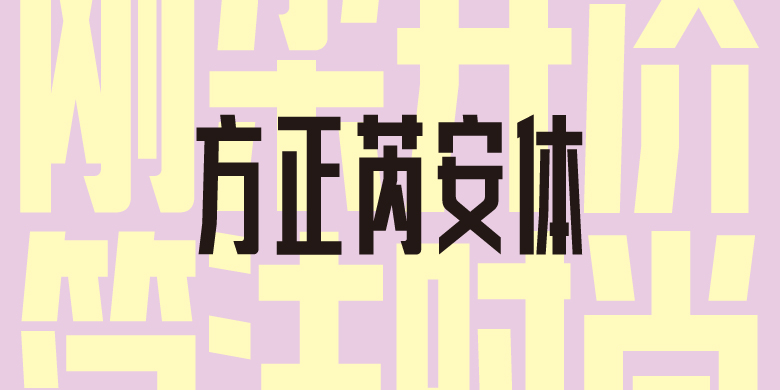
方正芮安体
朱进
黑体、创意字体
整体是平面方块形,重心瘦高偏上,中宫外扩,使字体更加饱满,视觉重心感强。切角与圆角的应用,使字体既时尚又体现出刚柔并济气质之美,而且字体给人一种充满生机蒸蒸日上的感觉。“芮”小草初生的样子,以“芮”字命名意为积极向上、富有生机,拥有着未知且充满惊喜的未来。适用于品牌包装、LOGO、海报、网页、广告宣传、标语、企业名称、展览等领域。